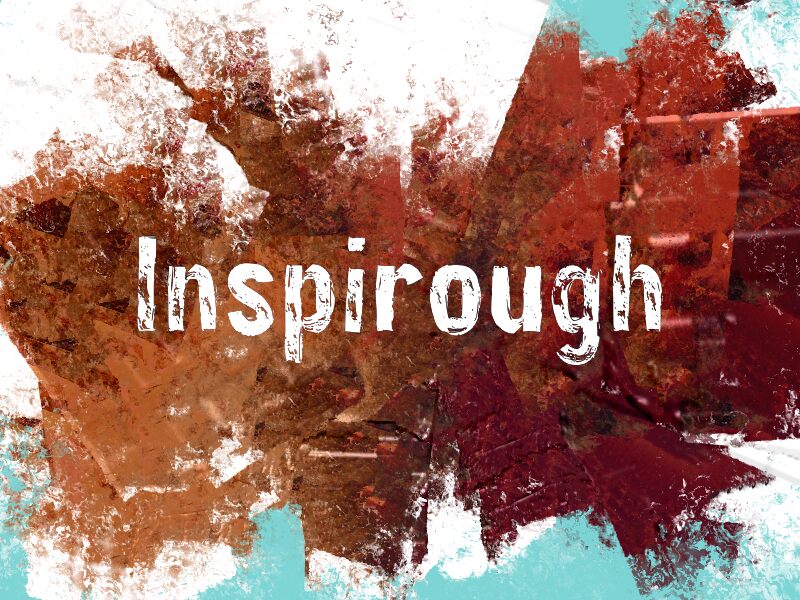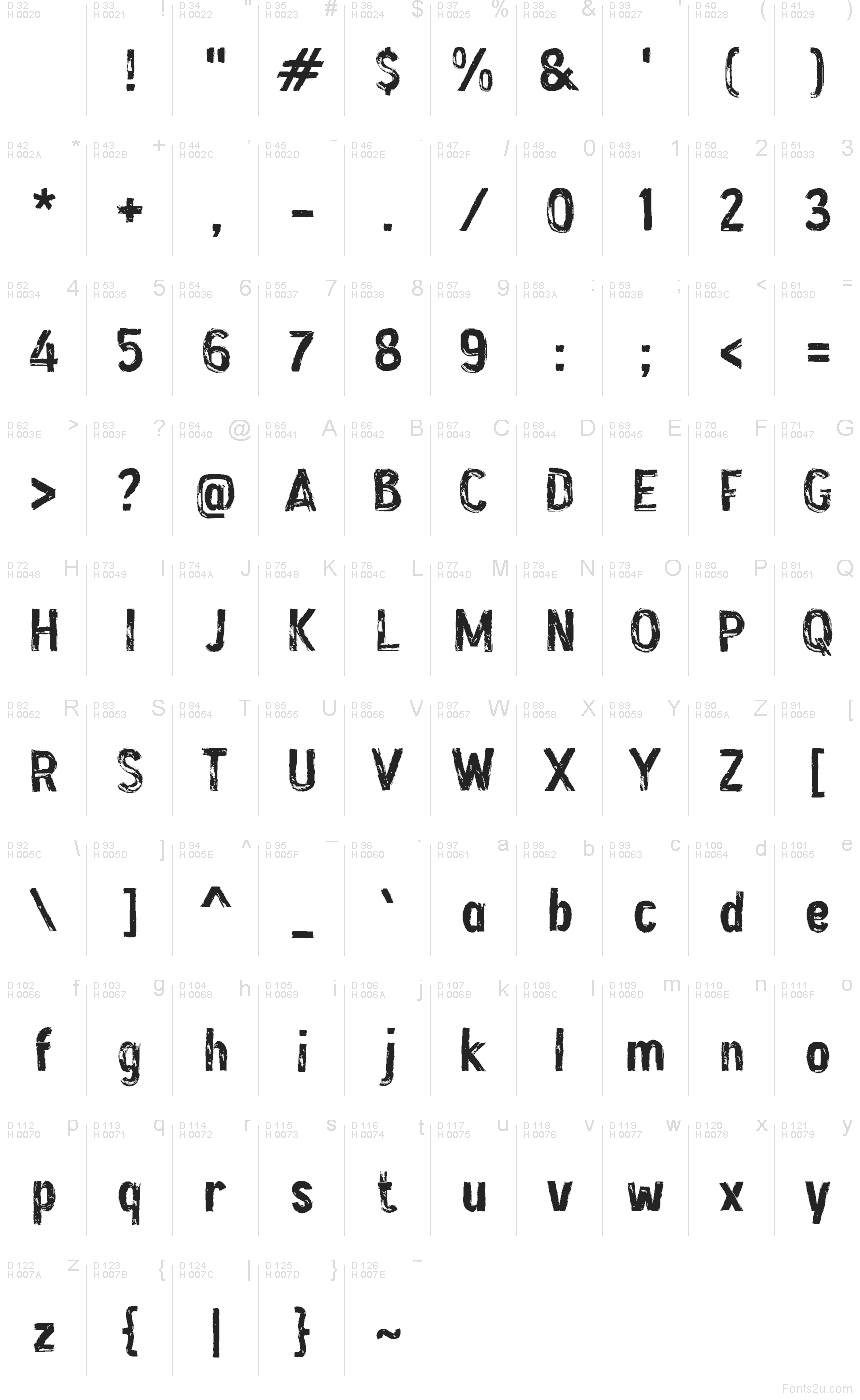
Inspirough od Wep je bezplatné, erodované písmo typu display, které se vyznačuje drsnými svislými škrábanci a polámanými okraji. Díky tomu vypadá každé písmeno jako ošoupané, nikoliv jen uměle zestárlé. Textura se v celém návrhu opakuje v dlouhých pruzích a vyštípaných místech, což písmu dodává vzhled opotřebovaného tiskového povrchu místo jemného vintage efektu.
Tato drsná textura se skvěle hodí na plakáty, obaly alb nebo mixtapeů, skate ziny, letáky na akce a titulky, které vyžadují syrový tiskový vzhled. Nejlépe vynikne u krátkých nadpisů a v logotypu, kde opakující se oděrky dodávají velkým písmenům výrazný grafický charakter, aniž by písmo muselo působit příliš jemně.
Inspirough